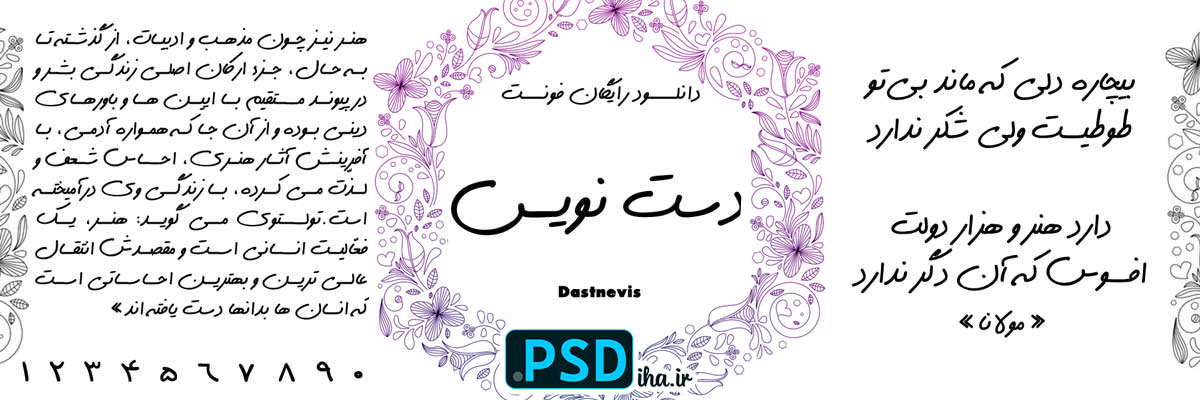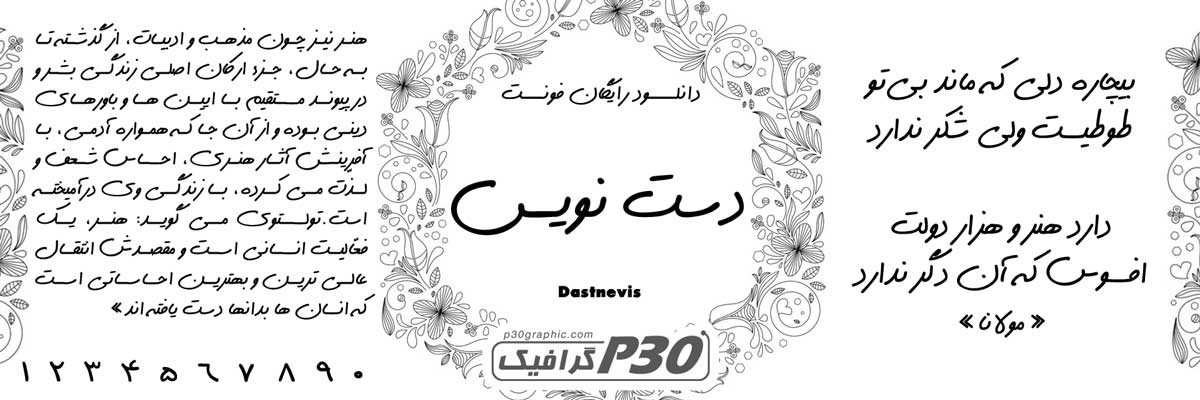
دانلود فونت دستنویس رایگان
فونت دست نویس
دانلود رایگان فونت دستنویس: حس گرم دست‌ساز در طرح‌های شما
سلام دوستان هنرمند! اگه مثل من عاشق فونت‌هایی هستید که انگار با قلم و جوهر روی کاغذ کشیده شدن، فونت دست نویس رو حتماً امتحان کنید. من خودم تو پروژه‌های چاپی شخصی‌م، از دعوت‌نامه‌های عروسی گرفته تا کارت‌های ویزیت هنری، بارها از این فونت استفاده کردم و هر بار حس می‌کنم طرح‌م یه نفس زنده گرفته. این فونت فارسی، با خطوط نرم و نامنظم‌ش، یه حس صمیمی و دست‌ساز می‌ده – انگار خودتون نوشتیدش! تصور کنید متن یه تراکت تبلیغاتی یا لیبل یه دفترچه خاطرات با فونت دستنویس؛ مخاطب‌ها فوری جذب اون گرمای انسانی می‌شن و طرح‌تون رو فراموش‌نشدنی می‌کنن.
چرا فونت دستنویس برای چاپ‌های خلاقانه عالیه؟
این فونت، با طراحی الهام‌گرفته از دست‌خط‌های واقعی، تو پروژه‌های گرافیکی مثل کارت‌های دعوت، تراکت‌های شخصی، لیبل‌های محصولات دست‌ساز و حتی پوسترهای هنری می‌درخشه. خوانایی‌ش تو اندازه‌های متوسط عالیه و با نرم‌افزارهایی مثل ایلاستریتور یا فتوشاپ، بدون هیچ مشکلی کار می‌کنه. نامنظمی ملایم‌ش، یه لایه احساسی اضافه می‌کنه بدون اینکه خوندن رو سخت کنه – ایده‌آل برای چاپ روی کاغذهای بافت‌دار یا براق. یادمه یه پروژه برای یه کافه هنری داشتم؛ با فونت دستنویس، منوی‌شون رو طراحی کردم و چاپ نهایی انقدر گرم و دعوت‌کننده بود که مشتری‌ها عکس‌ش رو تو اینستا شیر کردن. حالا دیگه تو هر طرحی که بوی خلاقیت و صمیمیت بده، اول سراغ این فونت می‌رم!
فونت دستنویس، با خطوط نرم و دست‌مانند، همه نیازهای طراحان رو پوشش می‌ده. وزن متعادل‌ش برای متن‌های اصلی و تیترهای کوچک مناسبه. انحناهای طبیعی‌ش، حس اصالت می‌ده. با فونت‌های دیگه ترکیب می‌شه و برای کارهای شخصی‌سازی‌شده عالیه. اگه می‌خواید طرح‌هاتون از دیجیتال به انسانی برسه، این فونت بهترین انتخابته!